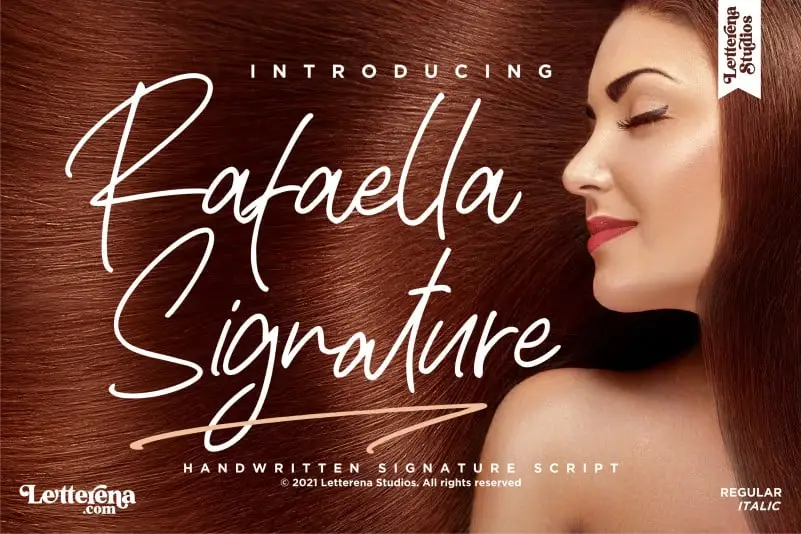
Rafaella Signature Script Font – Download Grátis
A fonte Rafaella Signature Script é uma elegante opção para designers aventureiros que buscam capturar um toque sofisticado em seus projetos criativos. Desenvolvida pela letterenastudios, esta font é perfeita para qualquer projeto que valorize uma autenticidade romântica, seja ela o logo de uma marca inovadora, designs de decoração de casa, embalagens de produtos, ou até mesmo capas de livros e cartões de nome. Sujeitável a diversos usos, como os posters de um evento especial, selos para sua estação de correio ou até mesmo o design do seu próprio casaco de skate, Rafaella Signature Script é uma font que vai marcar seu trabalho com um toque autêntico e único. Com certeza, ela será a escolha perfeita para qualquer projeto que busque se destacar em sua categoria.